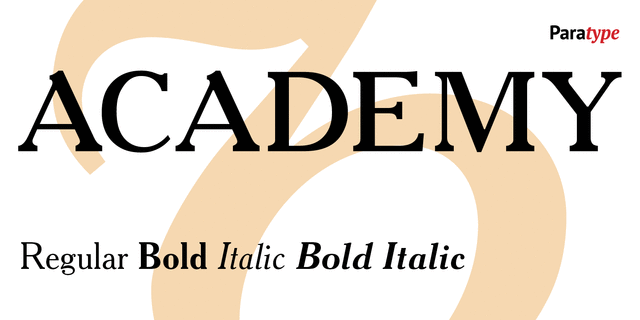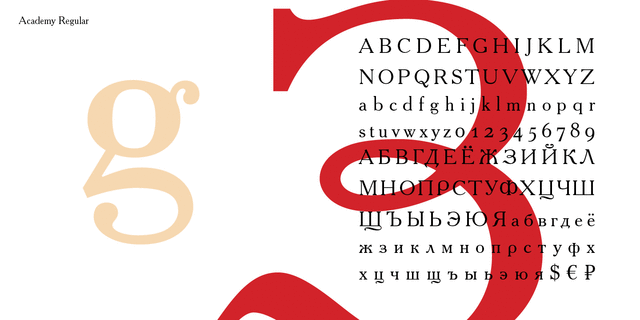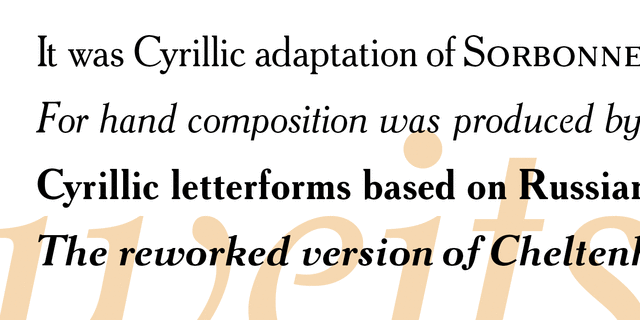
Гарнитура разработана в словолитном заведении Бертгольд (С.-Петербург) около 1910 на основе рисунков шрифта Sorbonne, 1905 (H. Berthold, Berlin), близкого к шрифту Cheltenham фирмы American Type Founders, 1896 (дизайнеры Бертрам Гудхью, Моррис Бентон), а также на основе русских шрифтов середины XVIII века. Малоконтрастный текстовой шрифт с историческим оттенком. Цифровая версия создана в Отделе наборных шрифтов НПО Полиграфмаш в 1989 году Любовью Кузнецовой. Корректировка и расширение гарнитуры проводилось в компании ПараТайп в начале 2000-х. Переработанная версия гарнитуры, в которую было добавлено жирное курсивное начертание, выпущена в 2009 году. В 2013 году выпущено расширенное нормальное начертание, в которое добавлены капительные знаки. Корректировки и расширения знакового комплекта выполнены Владимиром Ефимовым.
Ассоциации c начертанием Academy BoldКачества и характер:
авторитетный, классический, консервативный, традиционный, старомодный, ностальгический, настойчивый, интересный, уважительный, художественный, гуманитарный
Особенности семейства AcademyХит десятилетия:
Хит 1900-х Хит 1910-х Близкий исторический оригинал: